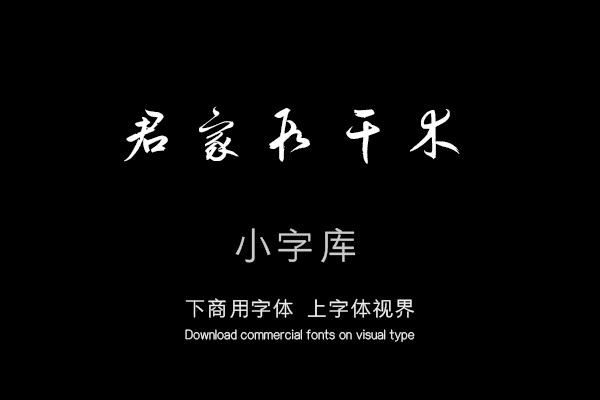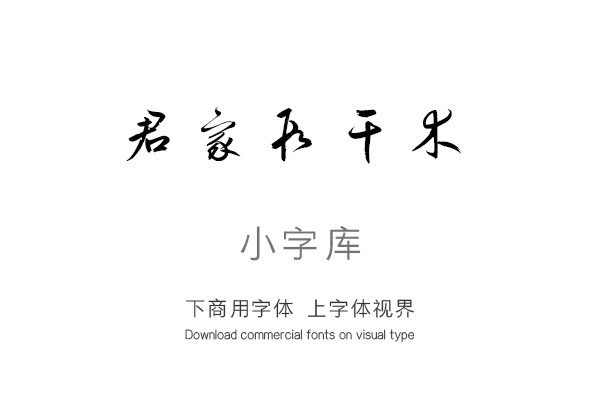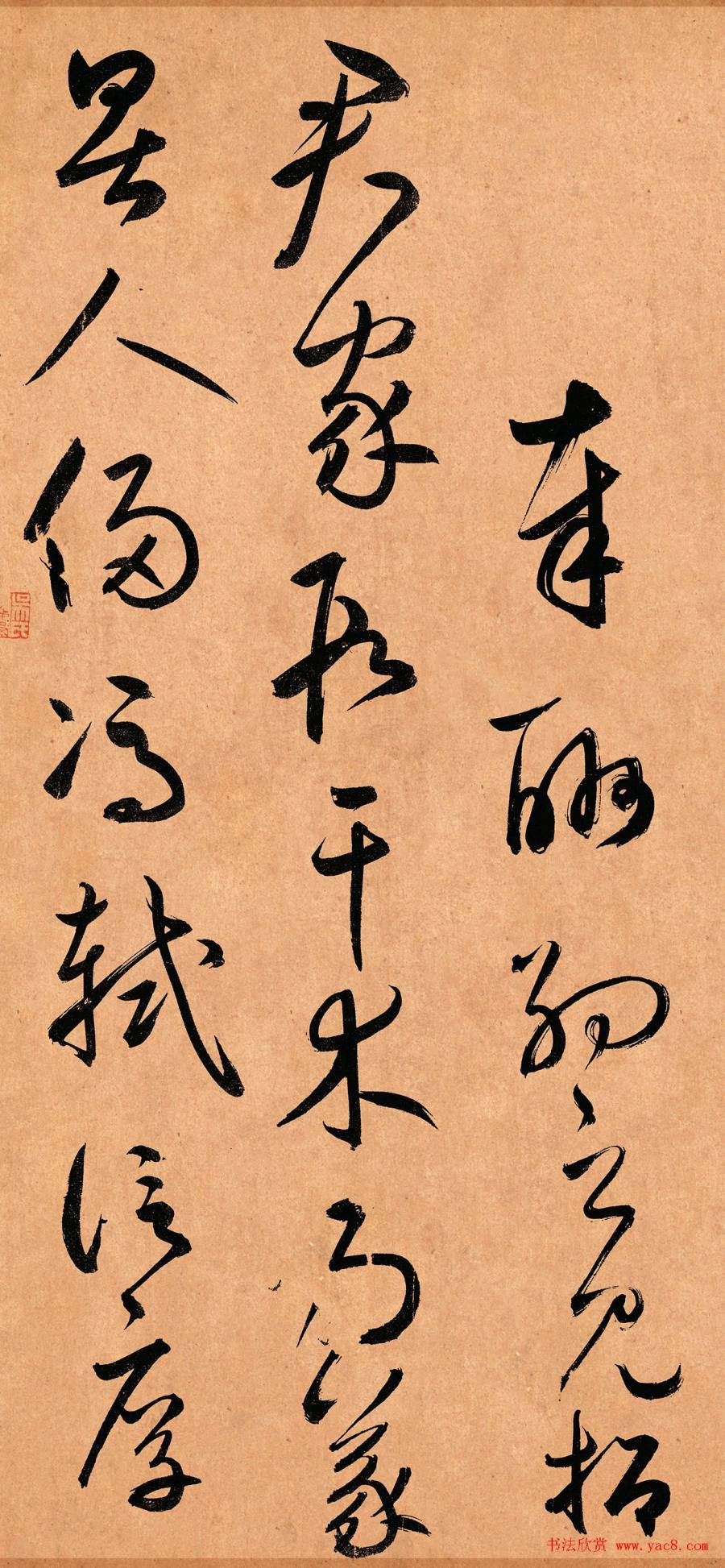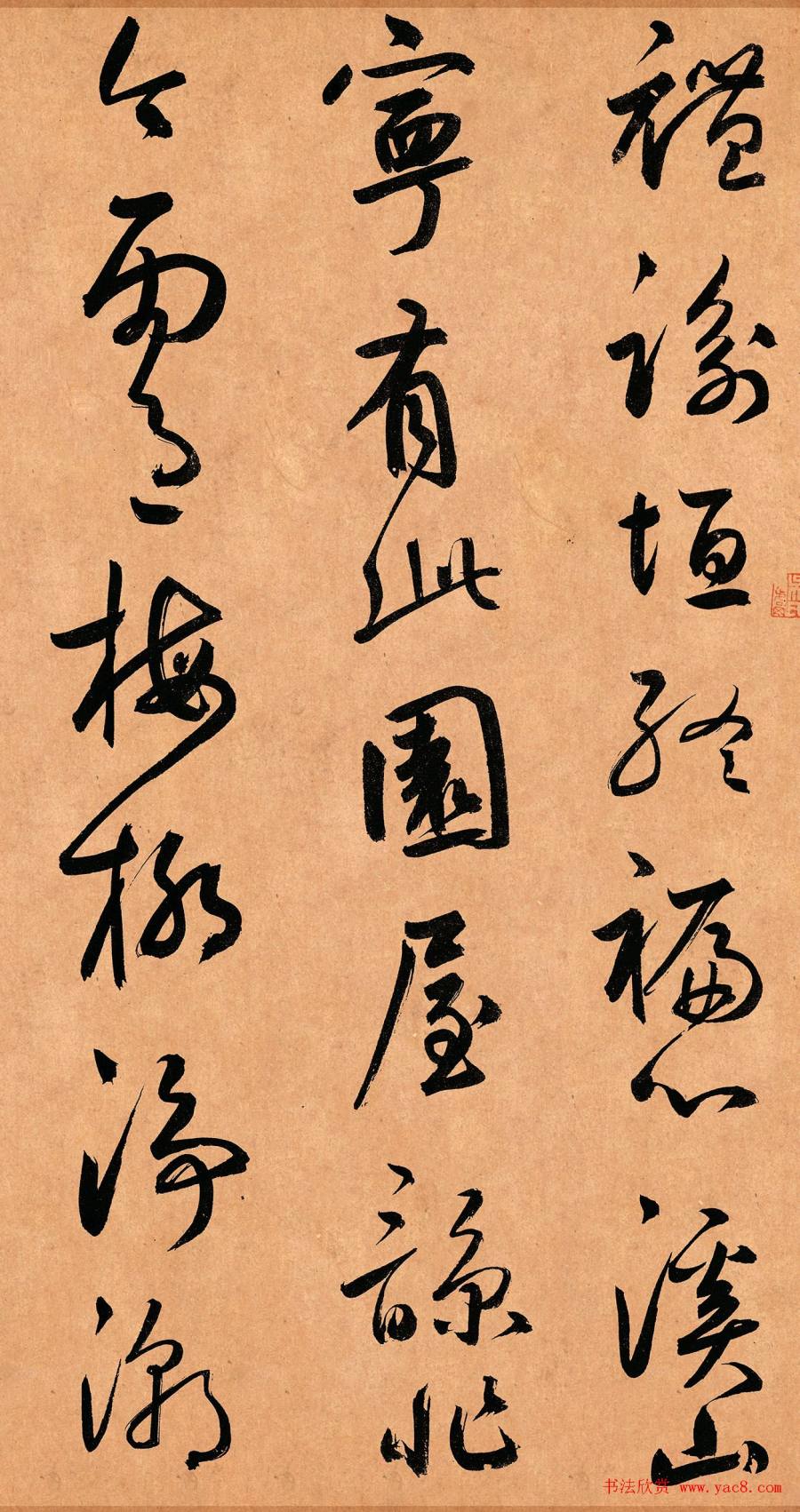
鲜于枢奉酬约之见招
《汉标鲜于枢奉酬约之见招》是一款根据元代鲜于枢行草书王安石杂诗《奉酬约之见招》,经过再次调整制作的小字库,该小字库共收录了该真迹作品中约174个字体。
奉酬约之见招 君家段干木,为义畏人侵。冯轼信厚礼,谕垣终褊心。溪山宁有此,园屋谅非今。雨过梅柳净,潮来蒲稗深。种芳迷近渚,伐翳不遥岑。清节亦难尚,旷怀差易寻。子猷怜水竹,逸少惬山林。况复能招我,亲题汉上衿。 右荆公杂诗。至元辛卯二月八日过君锡真味堂,出纸命书,遂为尽此。君锡书法得前人之正,又所收秘笈在诸家法帖上,亦须拙笔,亦爱忘其丑之意耶。鲜于枢记。